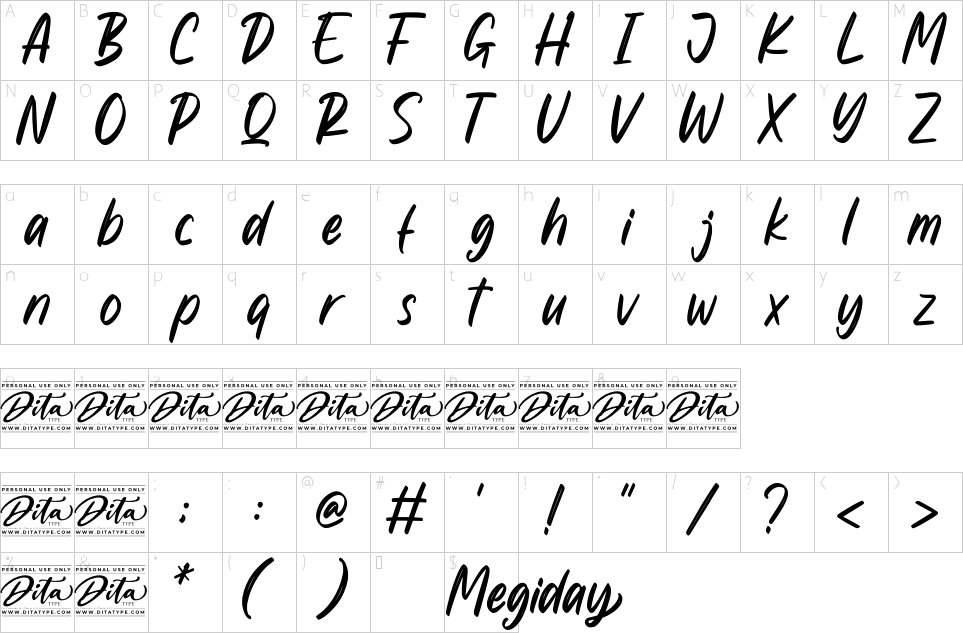
A Megiday Font é uma elegante seleção de caracteres que oferece uma variedade rica de opções para designers e criativos de todos os níveis. Desenhada pela Dita Type, esta fonte gratuita pode ser facilmente instalada no seu sistema Windows ou Mac, permitindo-lhe explorar sua vasta variedade de estilos, do elegante e sofisticado ao simples e minimalista. Com mais de 3.179 downloads, é evidente que a Megiday Font se destaca por sua facilidade de uso e grande quantidade de recursos disponíveis. Adicione seu próprio toque de criatividade a qualquer projeto com a Megiday Font, uma fonte de alta qualidade disponível sem custos.